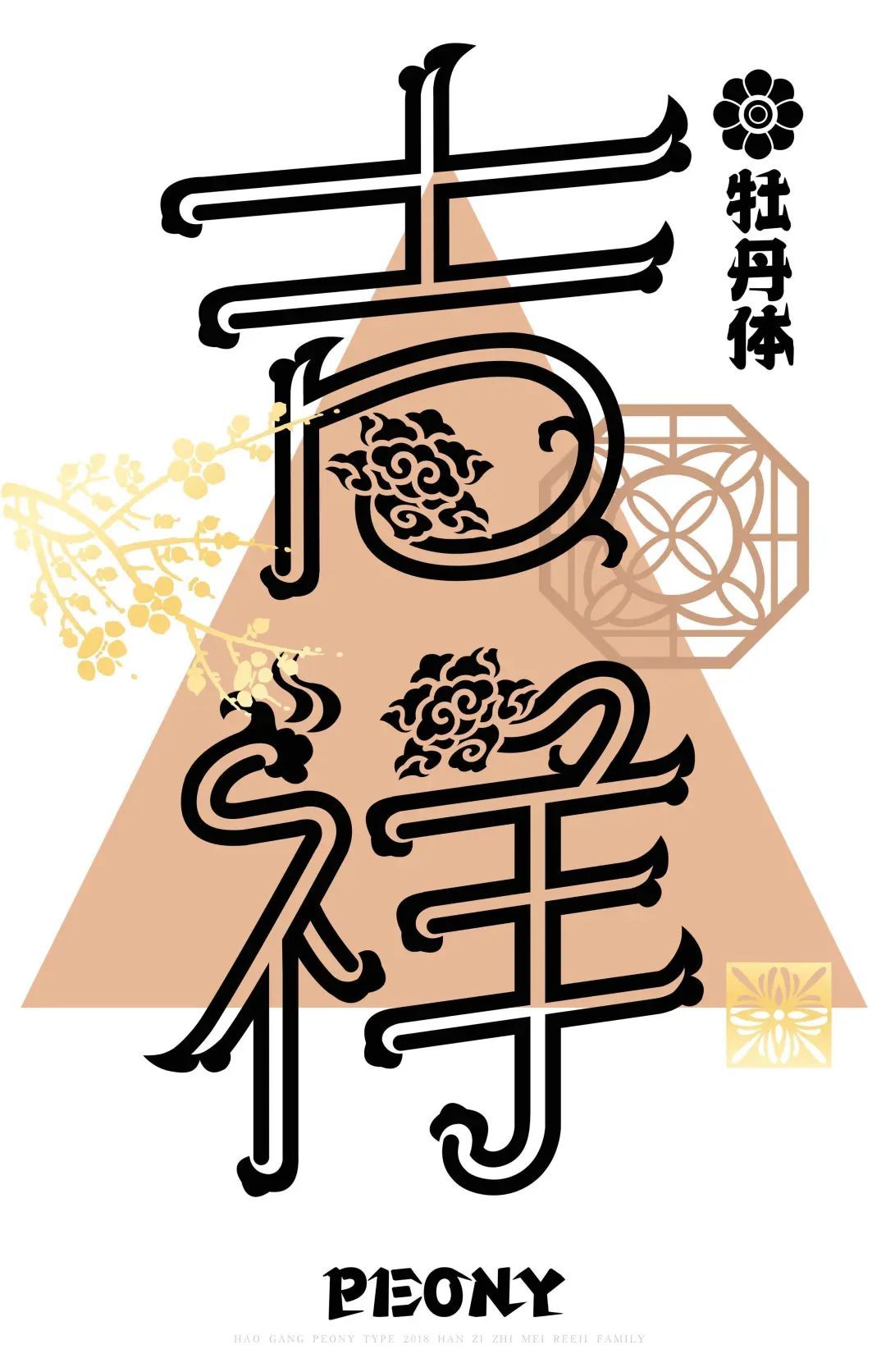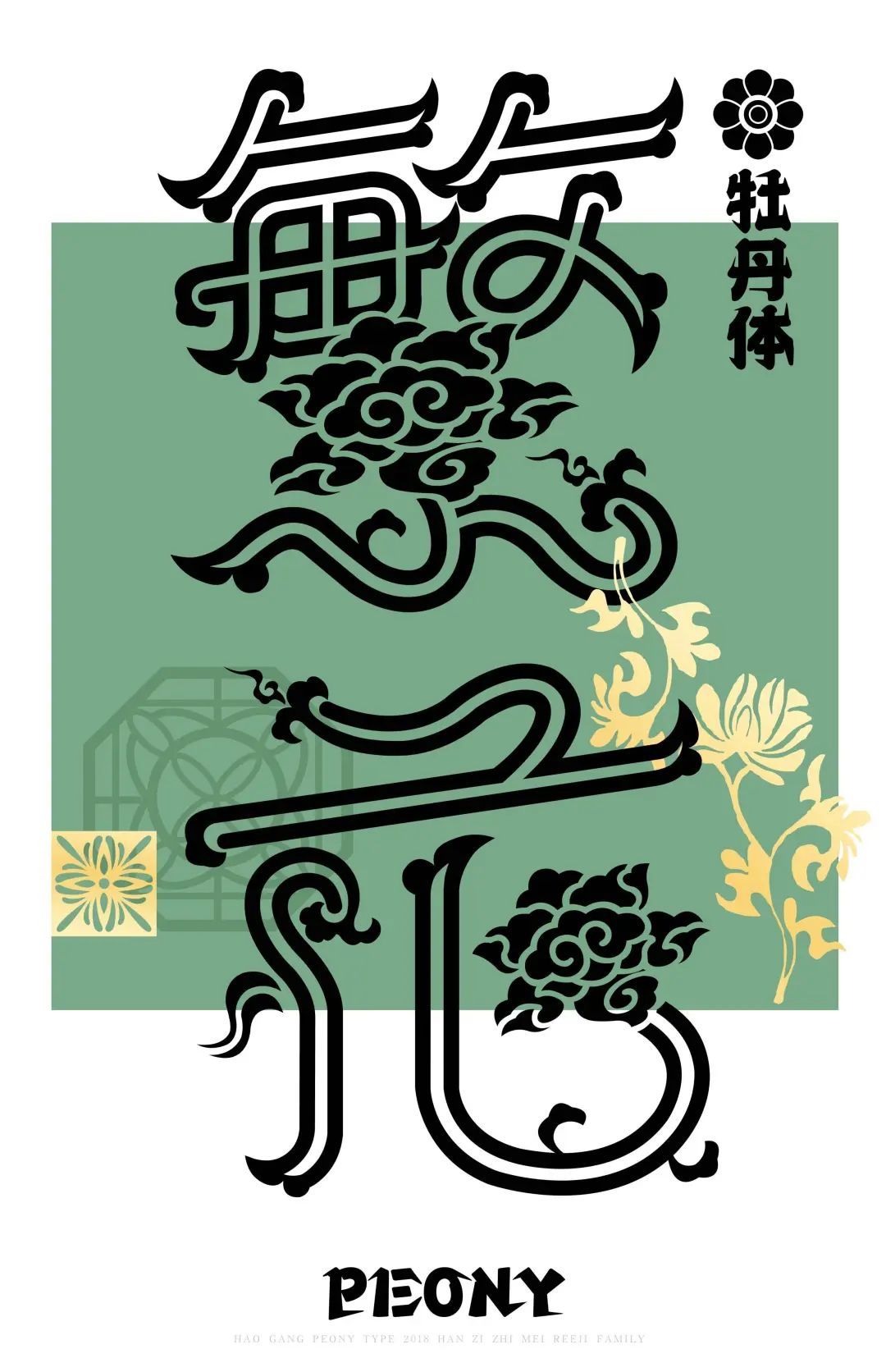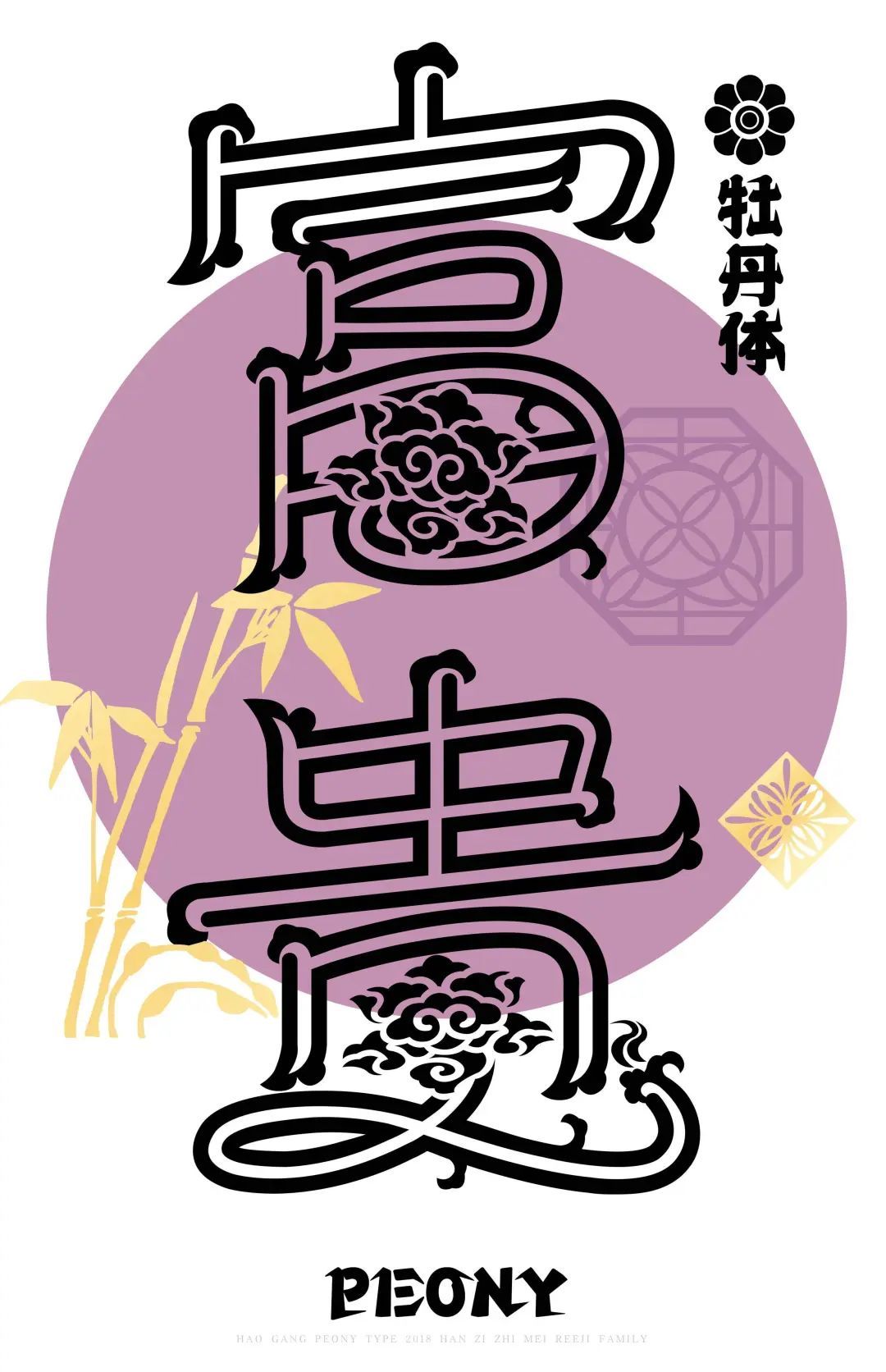
字造梦想 | 他让汉字生出了花儿
美的底层逻辑,是文化与秩序。从文化属性去解构汉字之美,是一项枯燥而繁复的工作。
对传统美学的敬畏、对汉字设计的热爱,是对冲的良药。今天跟大家分享一位深研非物质文化遗产装饰汉字二十多年的书体传承人——郝刚老师的故事。
01渊源
出生于艺术世家的他,在充满了浓厚艺术氛围的家庭熏陶下,从小就表现出过人的艺术天赋。毕业于吉林省戏曲学校舞台美术设计专业,之后又长期从事传统装饰与艺术设计工作。许是家庭的影响,或是对传统美学的痴恋,他开始将美学视角聚焦到装饰字体的创新创作之上。
潜心研究装饰字体设计,一做便是二十几年。所设计的《牡丹体》、《青铜体》、《文楷》、《凤书》、《字魂》、《字韵》为代表的装饰字体作品,屡获殊荣,获得专业奖项40余项。
特别是汉字之美郝刚牡丹体,将国花融入汉字的设计,是文化与字体的美学破壁,获得了美国Sparkawards铜奖、GDC优异奖、GRANSHAN全球第十届非拉丁文字体大赛提名奖等。
02传承
装饰汉字是汉字的装饰化、图形化艺术,是汉字书法与装饰艺术有机融合的独特艺术形态。从甲骨文创作到当代汉字设计,从象形到意会,从繁到简.......我们看到文字从图形又回到了图形。
这是文字经过历史的百转千回后,回归的初心。郝刚将这份对中国传统文字的理解和感悟,融入他的字体作品中,形成了他自己独到的风格,成为非物质文化遗产装饰汉字书体传承人。传统汉字经他的再创作,焕发了新的生命力!
03热爱
随着设计的应用多样化,字体设计似乎已然成为一种设计的时髦活儿。但专业的字体设计师会告诉你,这是一项枯燥到无底线的工作。
2018年国际文字设计协会主席Garry来北京,讲座结束后他问郝刚:“是什么动力能让你把《牡丹体》创意的如此完美”?郝刚答:“是热爱”,主席最后说:“你的这份热爱很伟大!”。就是这份热爱让郝刚跨越了一个个专业上的瓶颈……
创作牡丹体的时候,曾经因为疲劳过度导致右眼视网膜脱落。治疗期间,新字体的创作始终令牵挂,还未康复便拿着自己的作品找到余秉楠老师做指点。作为字体设计师通过做字库方式将作品留存在大众视野,是一件特别美好的事。
“国色天香”的牡丹,以其富丽、高贵和娇艳姿态赢得国人的喜爱,曾被作为“国花”之选。从古至今,千姿百态的牡丹不但作为绘画题材在历代国画中出现,而且从具象到抽象,不断地出现在建筑雕刻、器物装饰、锦绣编织的图案中。
这款字体的设计,正是选取明清饰锦的构成因素,又成为字体的点缀性装饰。字体以细线双勾的笔画拟为花枝,通过花枝笔形的流畅运行,连缀牡丹锦图案的花朵与花叶,共同构成字体的基本形态。展现出富丽堂皇、典雅高贵的风格。
04探索
对装饰字体的独特眼光和对文化传承的美学探索,使他成为非物质文化遗产装饰汉字书体的传承者。这是对传统美学的肯定,更是对造字人的一份鼓励。字敬传统,弘扬文化的系列汉字品牌创意作品,被广泛应用于政企标识及媒体传播。
高度概括的金、木、水、火、土抽象图形,巧妙地为标识蕴育出中华五行太极文化中博大精深、和谐众生的理念由五行构建多元的魁星楼,呈现出天圆地方、独占鳌头的宇宙世界观和文化内涵。